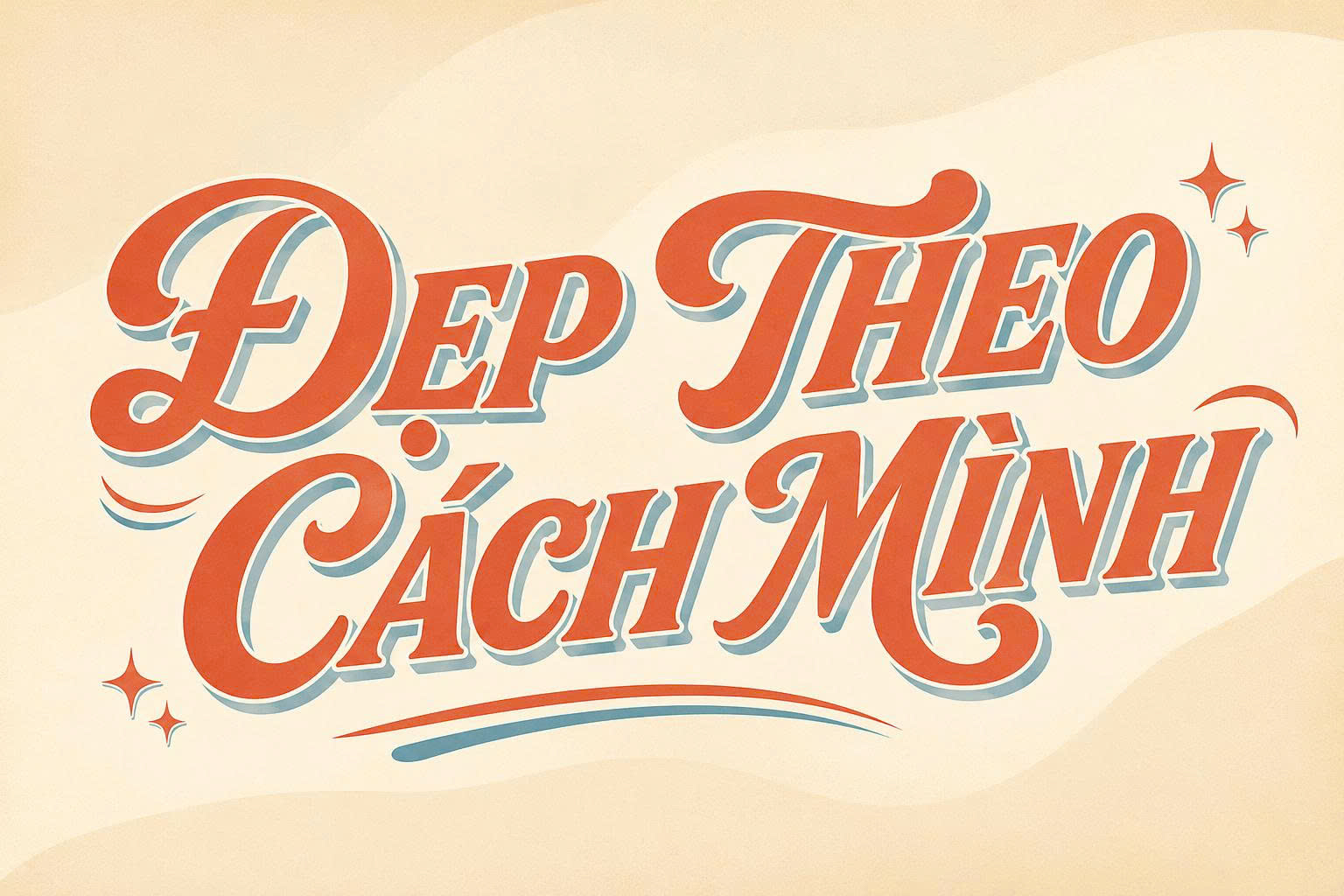
Font Retro Việt hóa là bộ sưu tập các phông chữ mang phong cách hoài cổ, tái hiện lại xu hướng đồ họa của những thập niên 70, 80 hoặc 90. Trong những năm gần đây, phong cách “Sài Gòn xưa” hay “Tiệm may cổ điển” đang trỗi dậy mạnh mẽ, khiến việc sử dụng font chữ vintage Việt hóa trở thành lựa chọn ưu tiên để tạo nên sự khác biệt. Doozypack.vn cung cấp link tải font retro Việt hóa chuẩn, hỗ trợ đầy đủ bảng mã tiếng Việt để bạn thiết kế bao bì, logo hay poster phim mà không gặp bất kỳ lỗi hiển thị dấu thanh nào.
Tại sao font chữ Retro Việt hóa lại là xu hướng thiết kế bao bì hiện nay?
Phong cách Retro/Vintage không chỉ là một trào lưu nhất thời, nó là cách thương hiệu kết nối với khách hàng thông qua những giá trị thuộc về cảm xúc và ký ức.
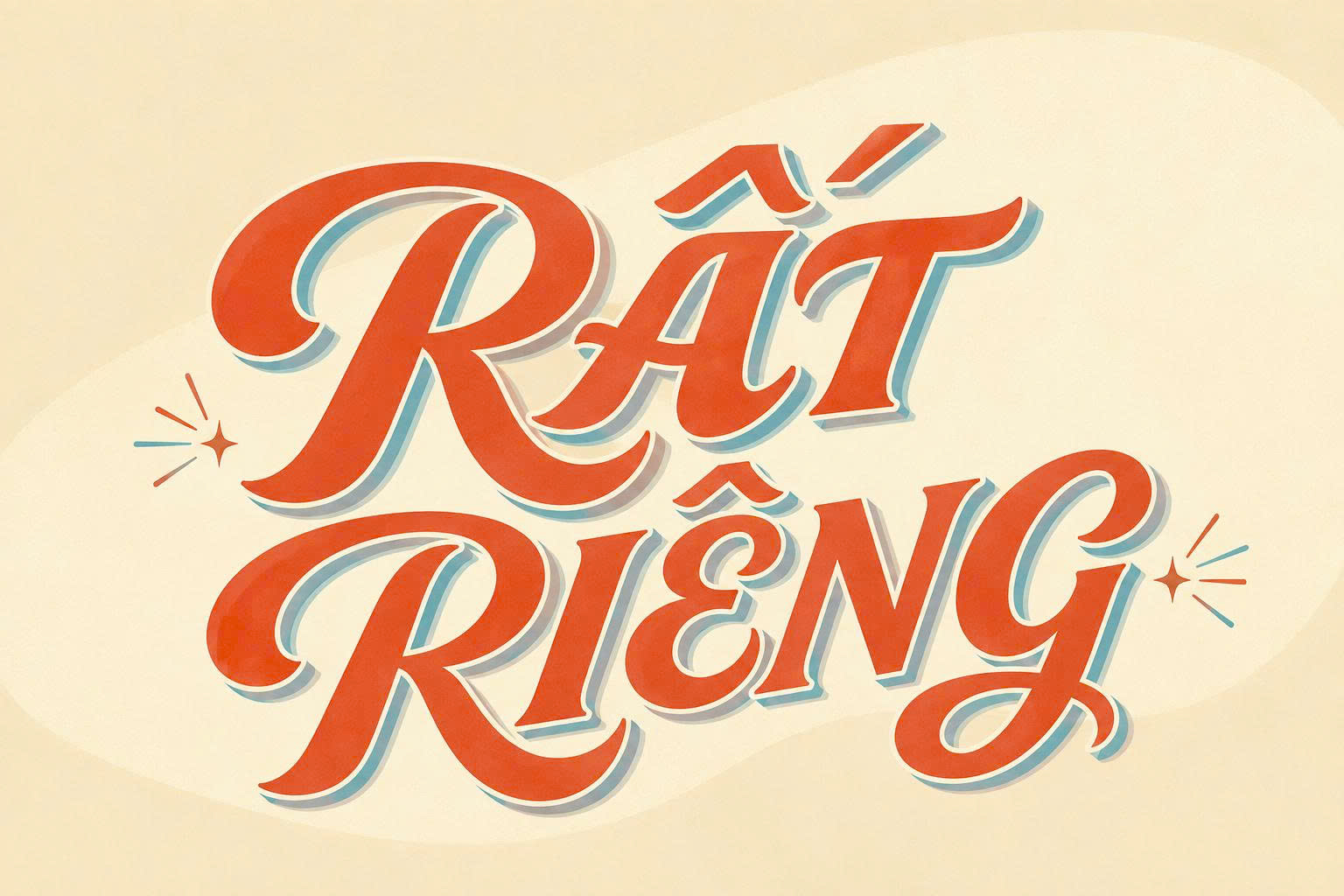
Khơi gợi ký ức và sự kết nối cảm xúc với khách hàng
Những bộ font việt hóa vintage mang lại cảm giác thân thuộc, gợi nhớ về những biển hiệu vẽ tay trên phố hay những tờ báo cũ. Khi khách hàng nhìn thấy một chiếc hộp giấy sử dụng font chữ hoài cổ, họ thường có xu hướng tin tưởng vào sự lâu đời và uy tín của sản phẩm, đặc biệt là các ngành hàng như thực phẩm truyền thống, trà hay cà phê.
Tạo nên dấu ấn thương hiệu độc bản
Giữa hàng loạt thiết kế hiện đại, sạch sẽ và tối giản, một bộ font chữ retro Việt hóa với những đường nét cầu kỳ, phá cách sẽ giúp sản phẩm của bạn nổi bật hoàn toàn trên kệ hàng. Sự kết hợp giữa nét cổ điển và tư duy thiết kế mới tạo nên một bản sắc thương hiệu riêng biệt, khó bị nhầm lẫn.
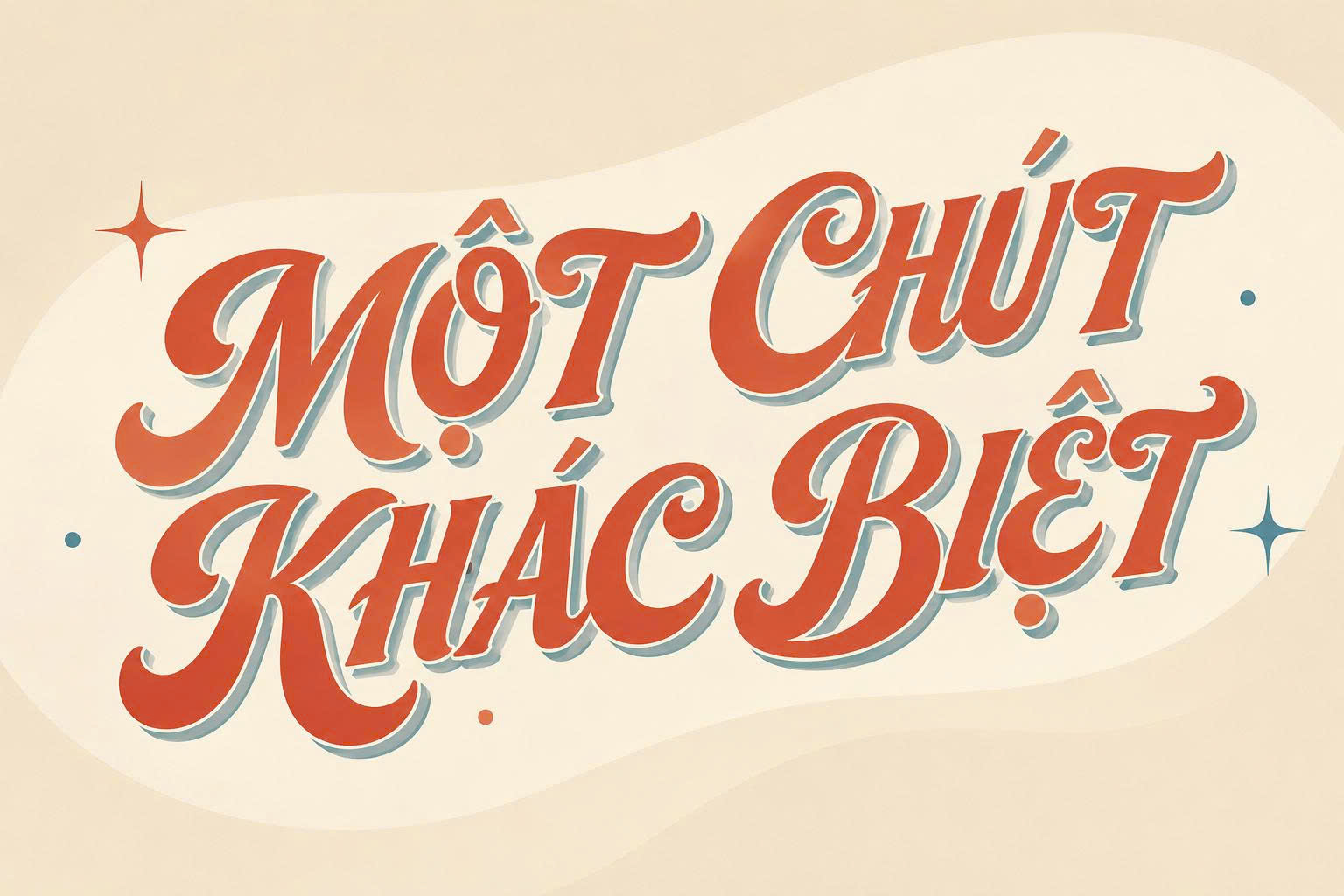
Đặc điểm của các dòng font chữ Vintage Việt hóa phổ biến
Tùy vào phong cách thương hiệu mà bạn có thể lựa chọn các font chữ vintage việt hóa free sau đây:
- Retro Font Script: Mô phỏng nét viết tay bay bổng bằng bút mực, thường thấy trong các quảng cáo nước giải khát hoặc thời trang thập niên 70.
- Retro Font Serif (Có chân): Mang lại cảm giác trang trọng, cổ điển của các tờ tạp chí cũ hoặc biển hiệu tiệm may.
- Font không chân dày (Bold Sans-serif): Vững chãi và mạnh mẽ, rất phù hợp cho các tiêu đề Poster sự kiện hoặc bìa sách hoài cổ.
- Hộp giấy đựng Cà phê & Trà: Sử dụng font chữ hoài cổ kết hợp với họa tiết vẽ tay mang lại vẻ đẹp đậm đà truyền thống cho sản phẩm.
- Túi giấy cho tiệm thời trang: Tên thương hiệu in theo kiểu vintage retro font giúp khách hàng cảm nhận được gu thẩm mỹ tinh tế của shop ngay khi cầm túi quà.
- Tem nhãn sản phẩm: Phù hợp cho các dòng mỹ phẩm thủ công, tinh dầu hoặc mứt trái cây handmade cần sự mộc mạc và gần gũi.
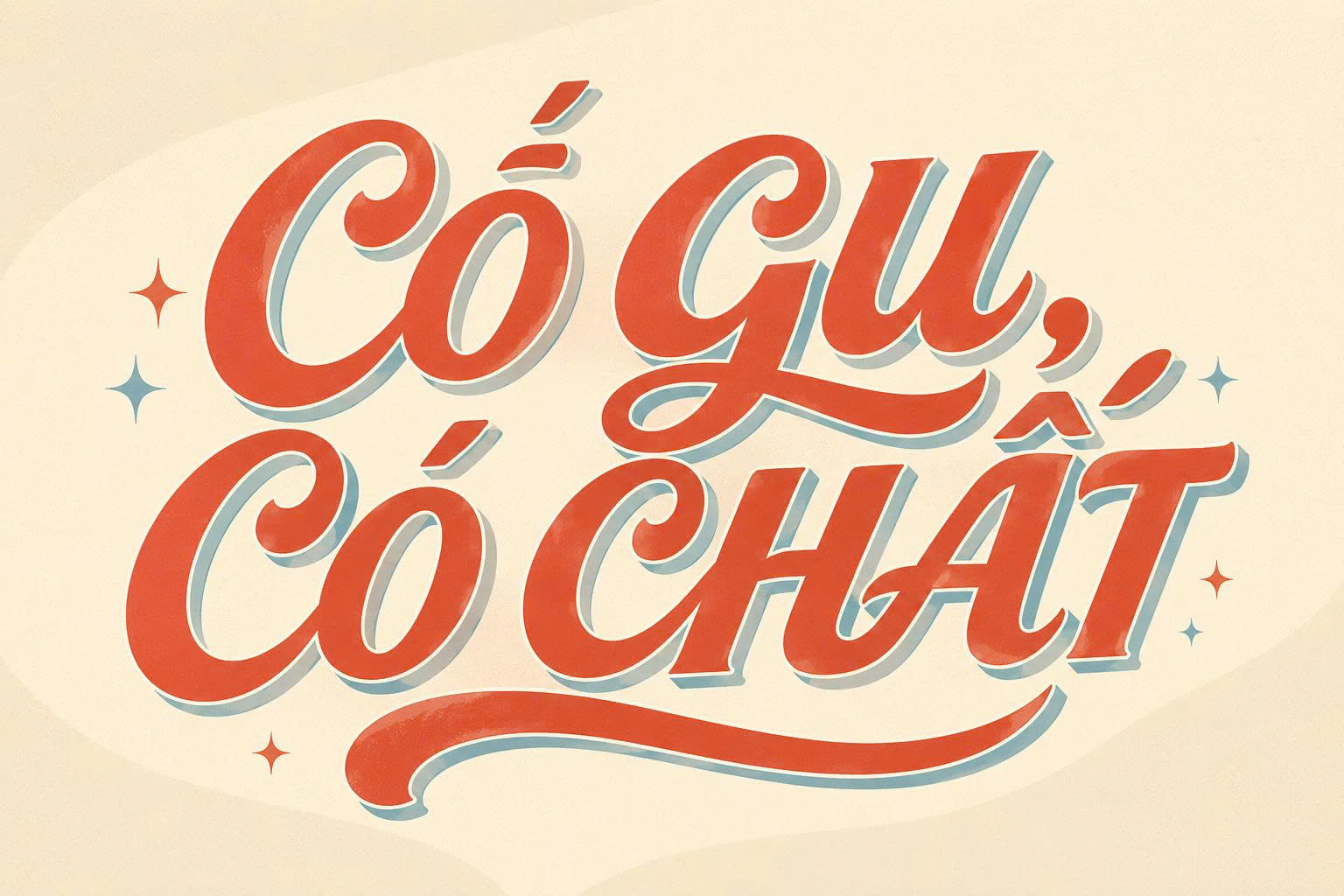
- Hệ màu CMYK đặc thù: Để có màu “retro” chuẩn, không nên dùng các màu quá tươi. Hãy pha thêm một chút tông vàng hoặc nâu để tạo hiệu ứng màu úa thời gian (Sepia) trên bản in.
- Lựa chọn chất liệu giấy: Font vintage sẽ phát huy tối đa vẻ đẹp khi in trên giấy Kraft hoặc giấy mỹ thuật có vân. Bề mặt giấy không bóng giúp nét chữ trông thật và có chiều sâu hơn.